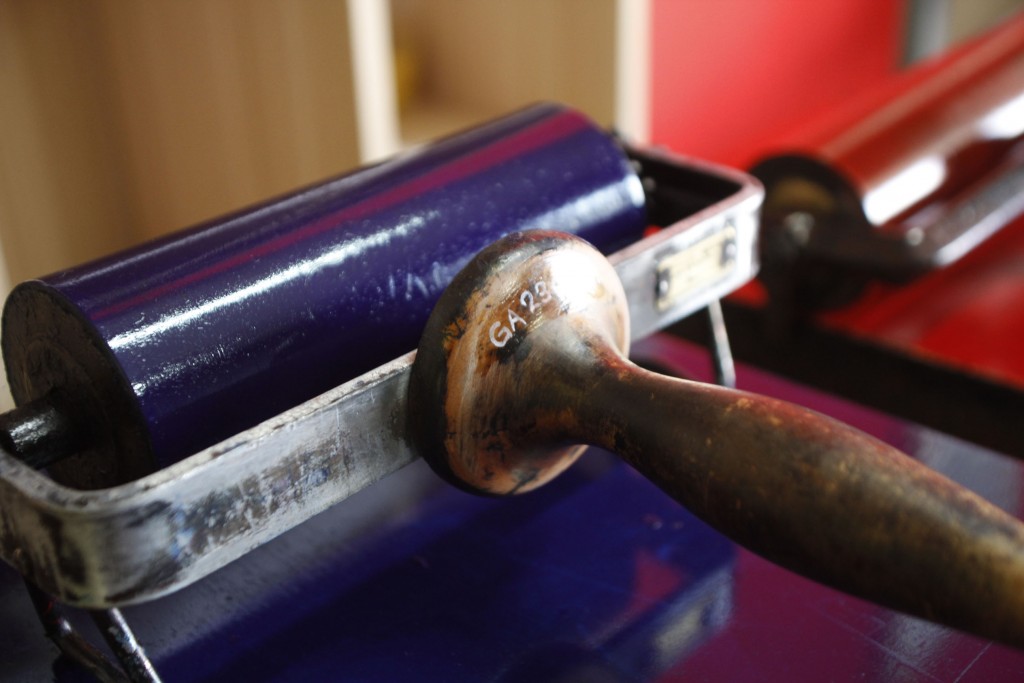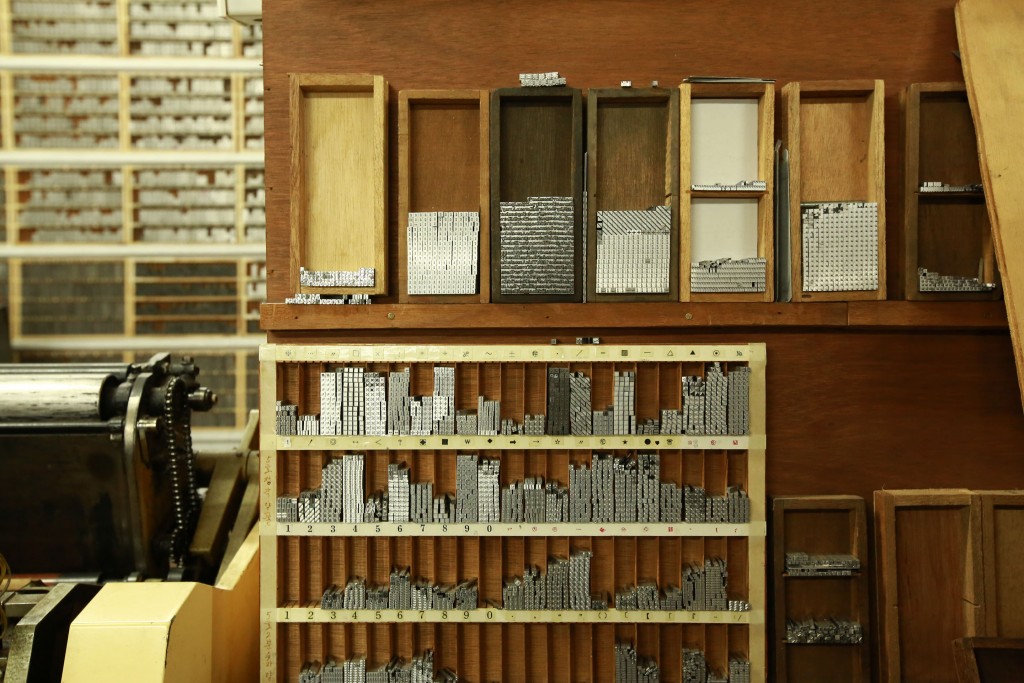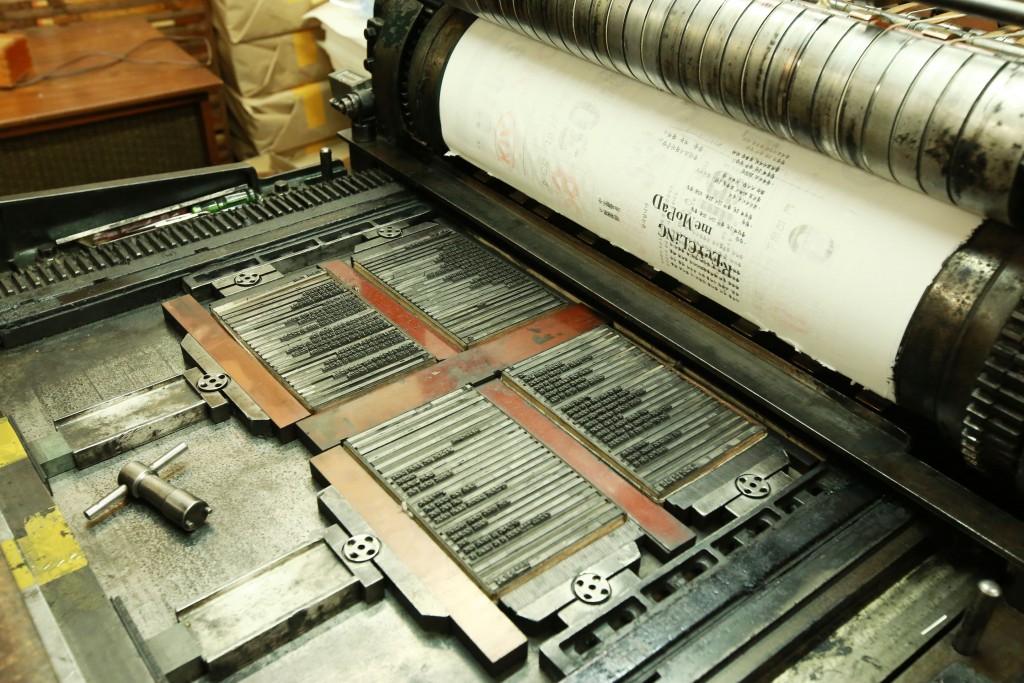
구텐베르크 특별전 : 동서양 인쇄술과 활자의 만남
500년 역사의 구텐베르크 인쇄술과 한국의 납활자 인쇄술이 만난다. 국내에서 유일하게 활판인쇄술을 보유한 파주 출판도시 ‘활판공방’과 독일 구텐베르크 박물관이 함께 준비한 ‘구텐베르크 특별전‘이다. 구텐베르크 인쇄기와 이 인쇄기로 만든 아름다운 책들을 만날 수 있는 자리로, 5월 12일부터 6월 12일까지 활판공방에서 열린다.
구텐베르크 특별전 : 동서양 인쇄술과 활자의 만남
5월 12일부터 6월 12일까지 파주 출판도시 활판공방에서 <구텐베르크 특별전>이 열린다. 500년 역사의 구텐베르크 인쇄기와 함께, 구텐베르크의 고향, 독일 마인츠 구텐베르크 박물관에서 온 주요소장품 73점도 함께다. 서양인쇄술의 혁명을 부른 구텐베르크 시대를 기준으로 전후 제작된 책이 중심이다.
가치가 8만 유로(약 1억600만 원)에 이르는 독일어 최초의 과학총람, 필경사와 도서화가들이 만든 ‘마인츠를 위한 예배서’와 ‘이솝우화’, ‘단테의 신곡’ 같은 문학책이 포함돼 있다. 필사본에서 인쇄본으로 넘어가는 시간 순으로 배치해 자연스럽게 지식과 사회문화사를 살필수 있게 했다. 무게만 1.3톤, 운반 후 독일 장인이 직접 조립한 구텐베르크 인쇄기는 구텐베르크 박물관 역사상 한국이 첫 해외 나들이다.
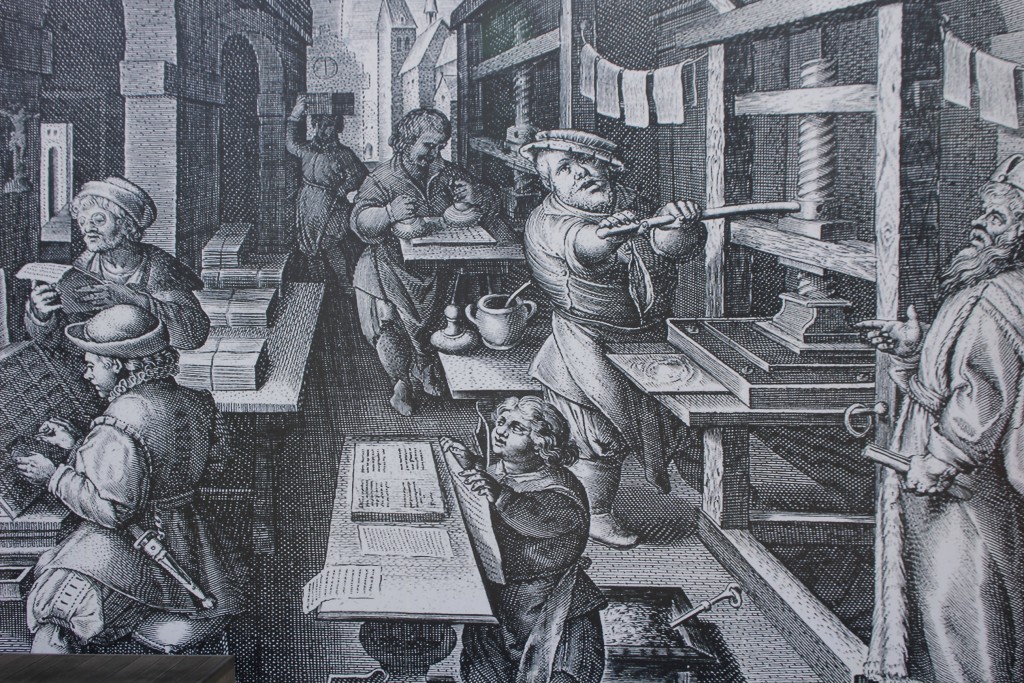
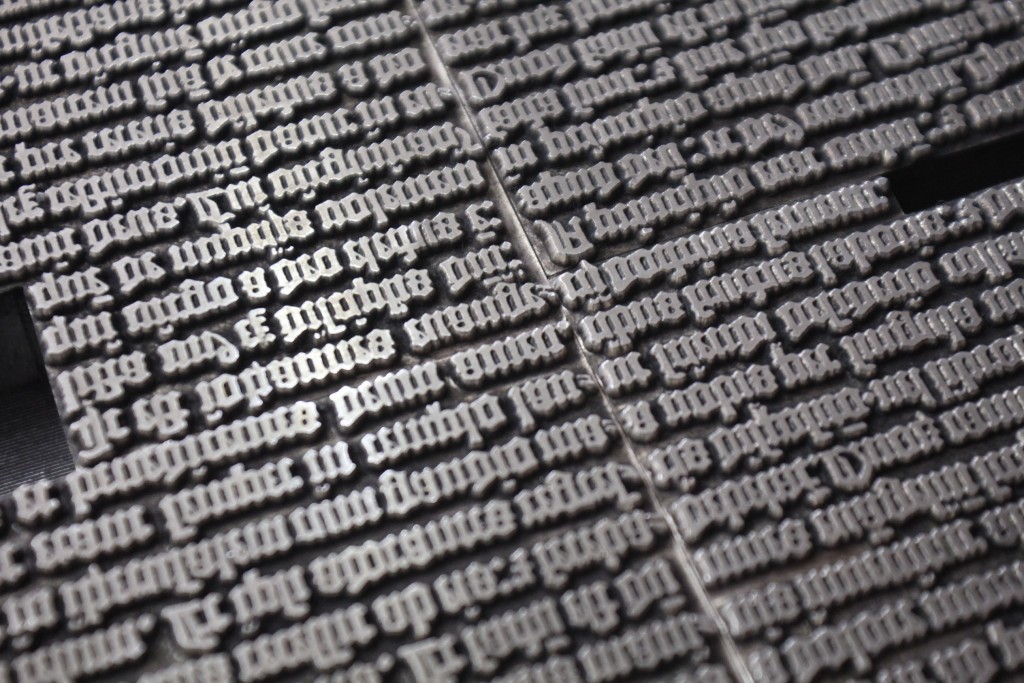
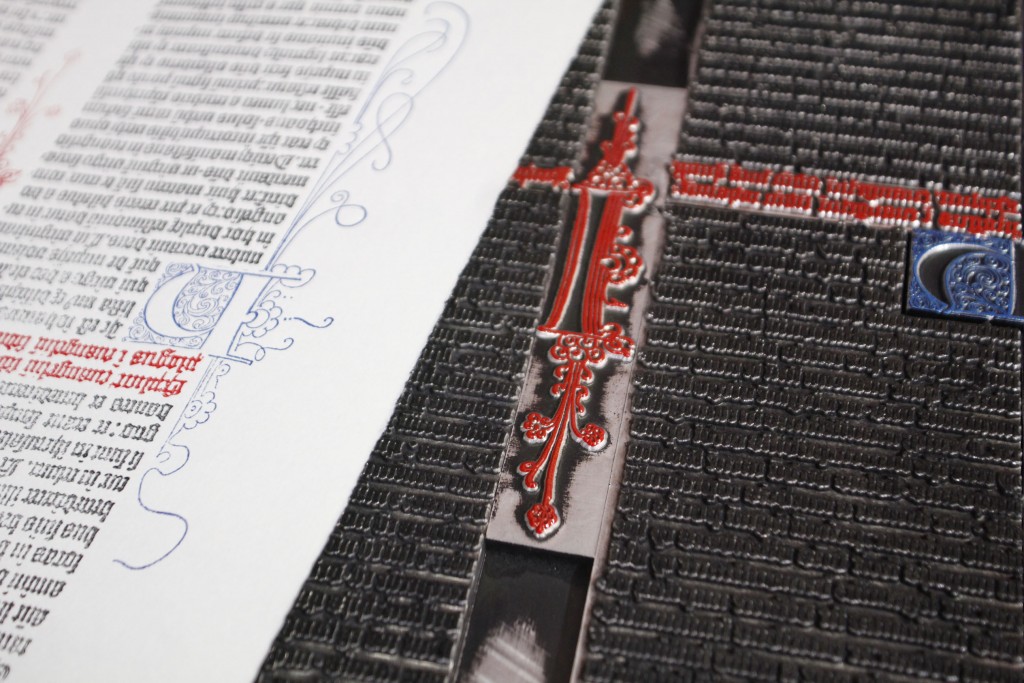
이번 전시를 기획하고 진행한 임진 객원 큐레이터는 ‘책 장식의 시각적 아름다움’을 강조했다. “이 시절 책은 귀족과 성직자들의 전유물이었어요. ‘책 장식’을 할 수 있다는 건 오늘날의 귀금속 액세서리만큼 부의 상징이었죠. ‘도서화가’들이 책의 여백을 장식하는 일을 했는데, ‘책이 이렇게까지 아름다울 수 있구나!’ 감탄하게 만듭니다.”고 말했다.
전시기간 동안 활판공방에서 준비한 유럽 레터프레스기로 구텐베르크의 ‘42행 성서’ 낱장을 직접 인쇄해볼 수 있다. 특별전시관과 동시에 운영하는 상설전시관에서도 한국의 고인쇄술을 재연한 활판책 제작과정을 체험할 수 있고, 한국의 활자와 인쇄의 역사를 한 눈에 돌아볼 수 있다.